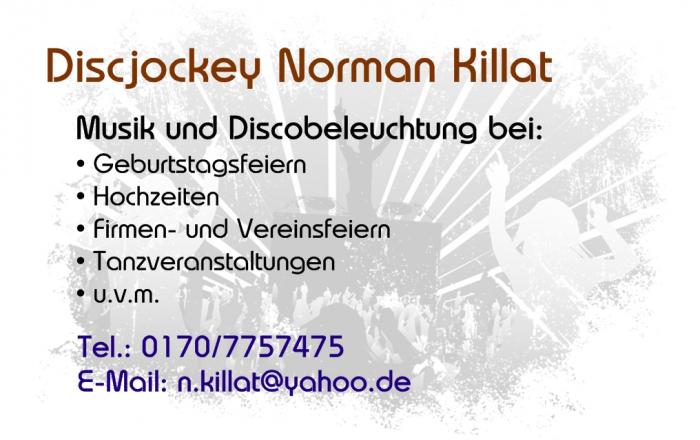
Schrift ähnlich wie Bauhaus und Pump???
Ich habe vor einiger Zeit eine Visitenkarte erststellt und weiß nicht mehr mit welcher Schriftart.
Die Schrift hat am meisten Ähnlichkeit mit Bauhaus und Pump, bzw. ist fast wie eine Mischung aus beiden.
Jedoch sind einige Buchstaben anders erstellt, als sie in beiden Schriften vorkommen. z. B.: "e" und "M"
Nun brauche ich die Schrift wieder, da sich die E-Mailadresse geändert hat!
Kann mir zufällig jemand sagen, wie die Schrift heißt?
Ja, Dessau kommt der Schrift von meiner Visitenkarte sehr nahe, selbst die Zahlen von Dessau sind genau wie auf der Visitenkarte! :rockon:
Jedoch das runde "r" und das "E" sind irgendwie wie von Pump. :-o
Kann mir zufällig jemand sagen, wie die Schrift heißt?
@ Norbert P: Von Harry Plain wurde für die von mir gesuchte Schrift anscheinend das "e" genommen und die Zahhlen kommen denen aus der gesuchten Schrift auch sehr nahe. Aber die offenen Stellen am "D" usw. sind bei Harry Plain nicht vorhanden.
Es schein wirklich nen Mix aus mehren Schriften zu sein. Ich würde sie ja versuchen aus Bauhaus, Pump und Dessau selbst nachzubauen, komme nur mit fontforge nicht zurecht.